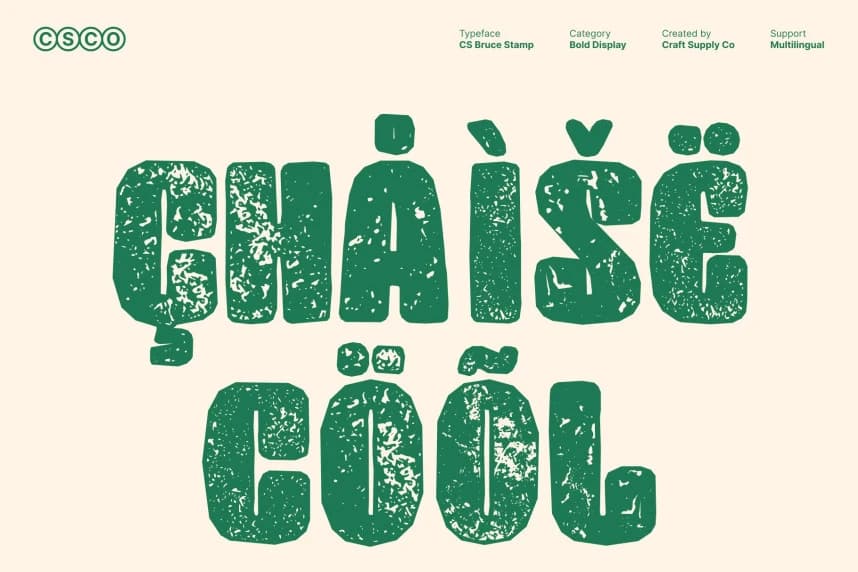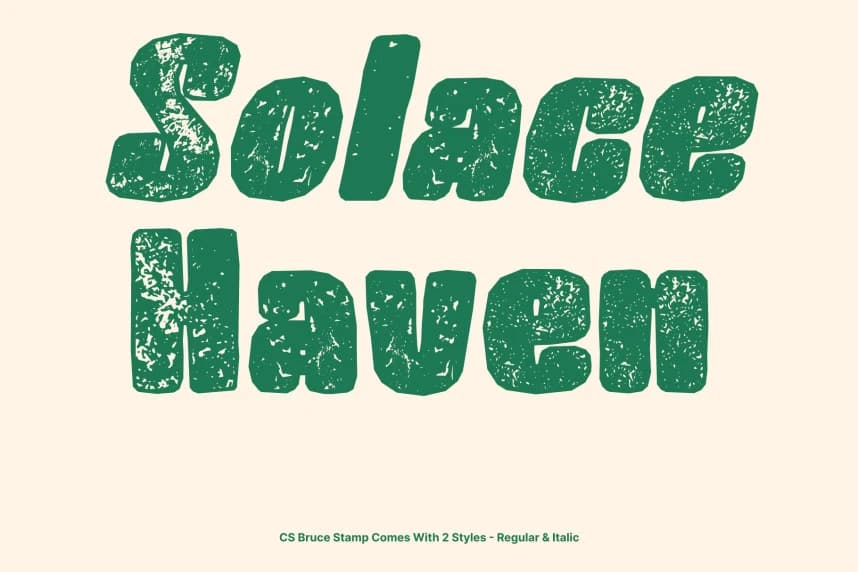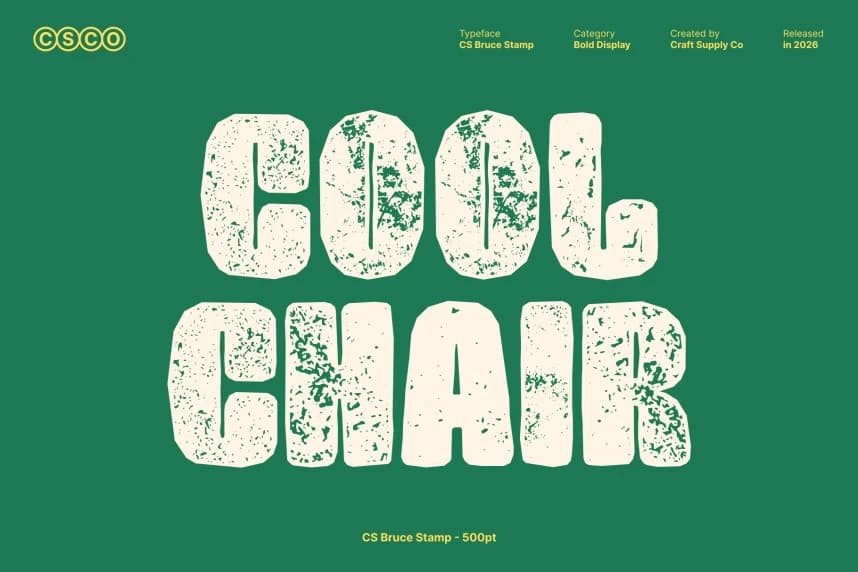
CS Bruce Stamp Yazı Tipi
CS Bruce Stamp Font – Dokuya Sahip Güçlü Bir Varlık ve Modern Çekicilik Sunan Kalın Gösterim Sans-Serif Yazı Tipi. Bu, temiz ve çağdaş bir estetikle üretilmiş, ilk bakışta güçlü bir görsel etki yaratmak üzere tasarlanmış bir kalın sans-serif yazı tipidir.
CS Bruce Stamp Font – Kalın Gösterim Sans Serif Yazı Tipi, dokulu güçle güçlü bir etkiye ve modern çekiciliğe sahip. Bu, temiz ve çağdaş bir estetiğe sahip olup, ilk bakışta güçlü bir görsel etki yaratmak üzere tasarlanmıştır.